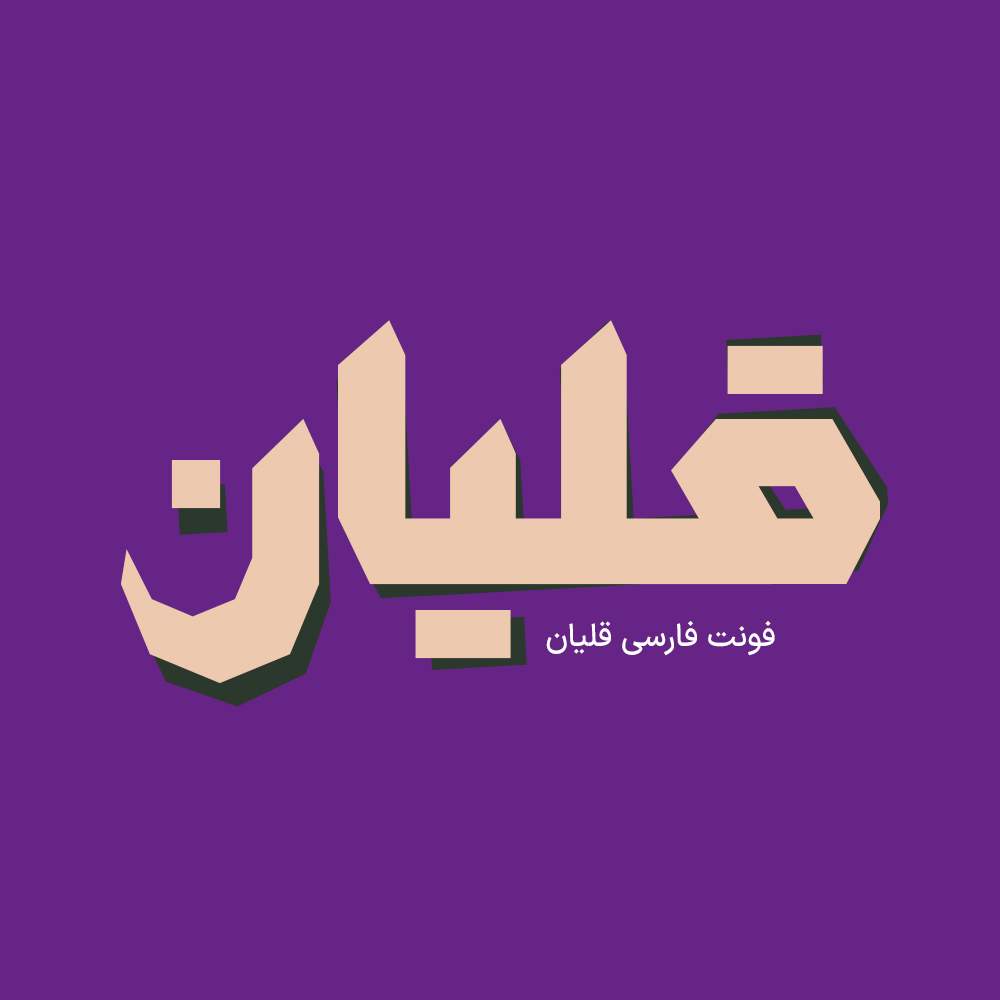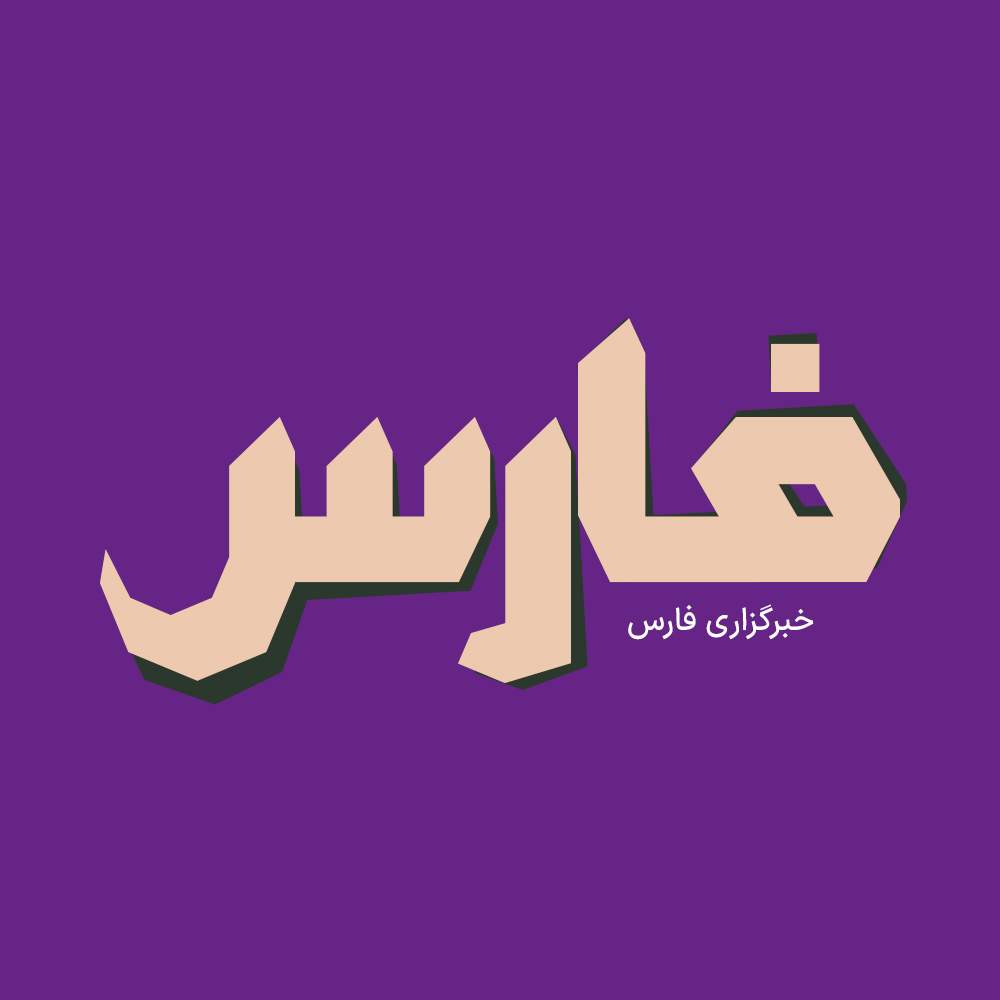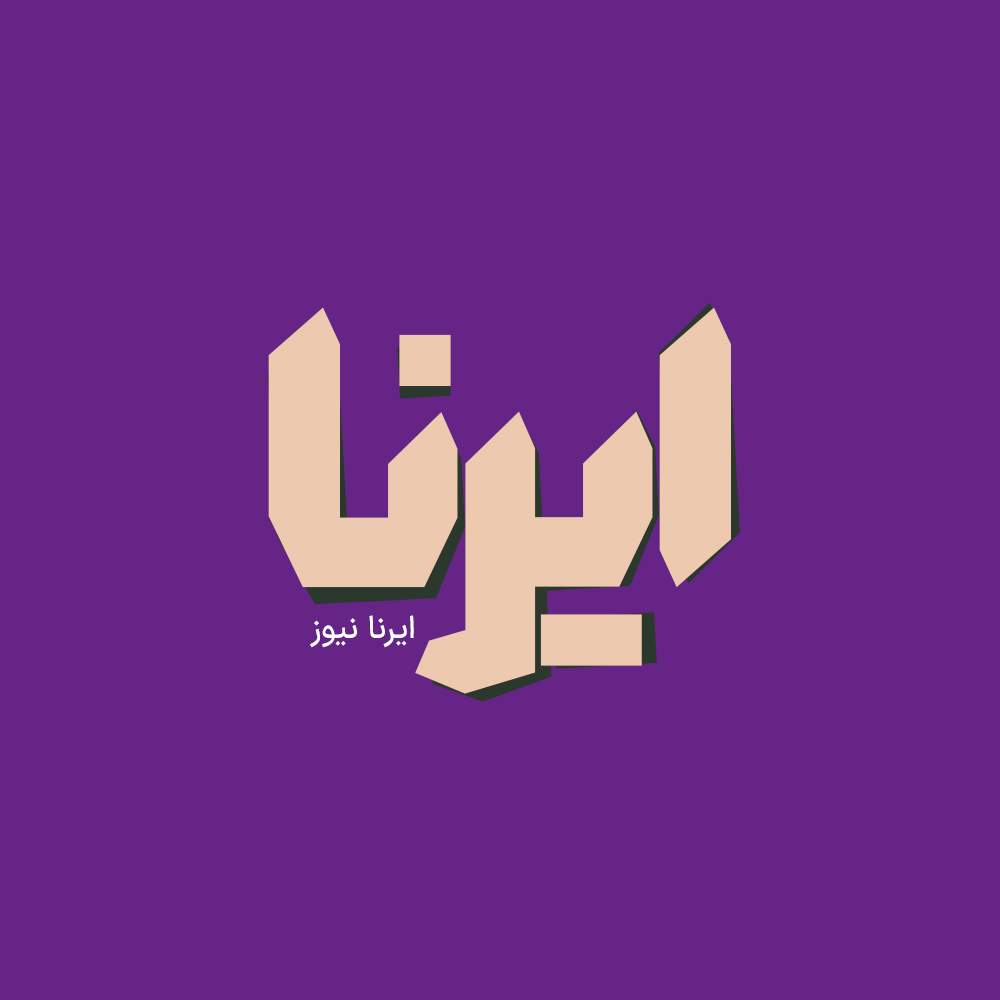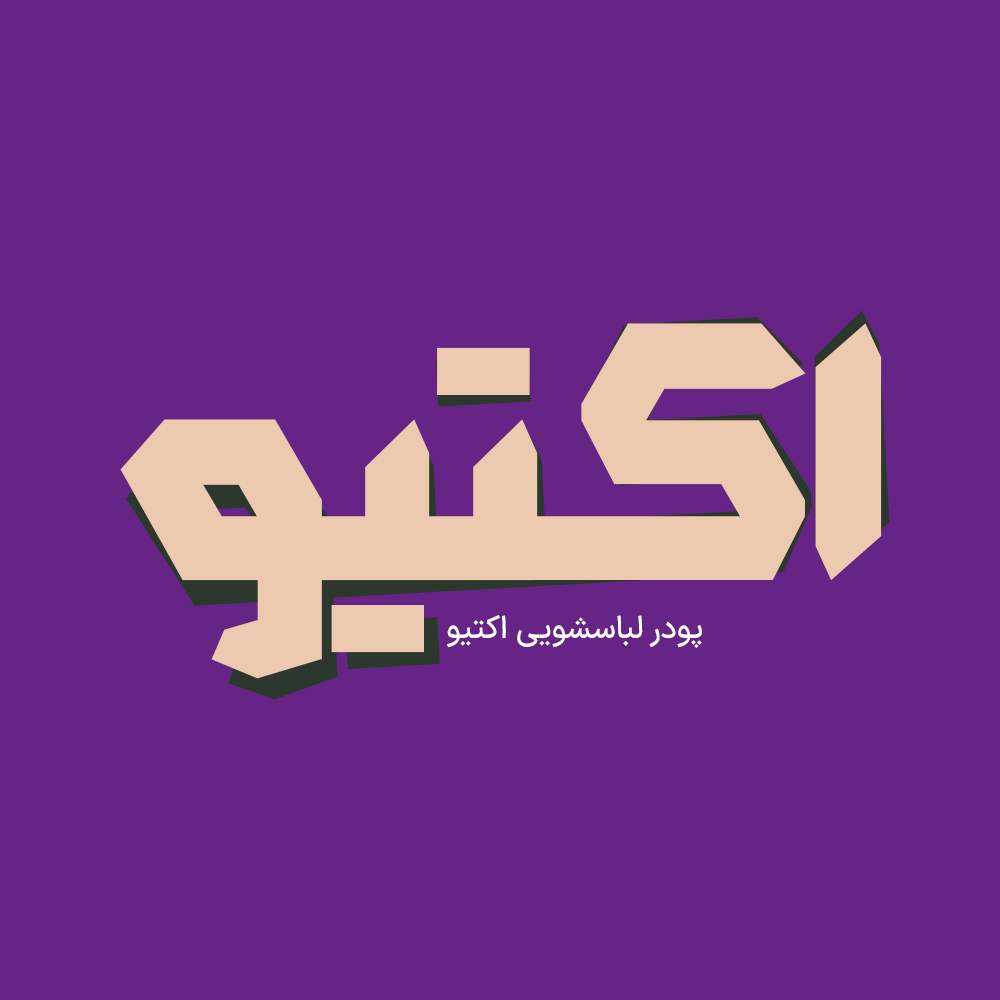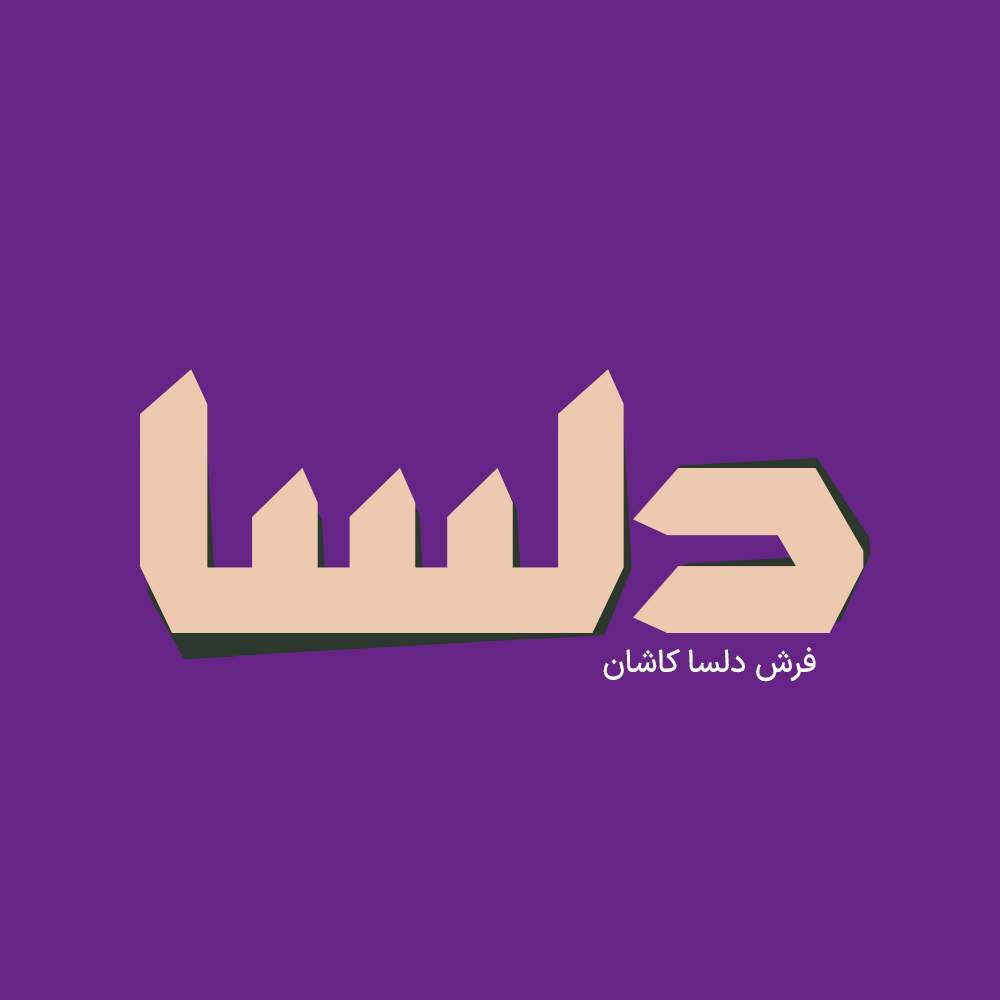
فونت فارسی قلیان از دسته فونتهای با بدنه قطور است. این سبک طراحی در حروفنگاریهای دهه ۴۰ و ۵۰ مرسوم بوده و فونتهای متعددی نیز در سالهای اخیر به این سبک ساخته شده است. تفاوت اصلی فونت فارسی قلیان با دیگر فونتهای این دسته، هندسه ساده و کنتراست ضخامت حروف است. فونت قلیان به سادگی در نرم افزارهای تحت ویندوز از جمله مجموعه برنامه های فتوشاپ، کورل، آفیس، اینشات و… قابل اجرا میباشد. طراحان وب سایت و گرافیست های خلاق می توانند از این فونت زیبا فونت در طراحی پروژههای تبلیغاتی و تجاری خود کمک بگیرند. فونت فارسی قلیان یک فونت تک وزن با کاربرد طراحی لوگوتایپ و طراحیهای مختلف همچون کتاب و تولید محتوای متنهای کوتاه و عناوین میباشد. در ادامه برای شما نمونه تایپ های این محصول حرفه ای رو آماده کردیم که میتونید مشاهده کنید.
پیشنمایش و نمونه تایپ های فونت قلیان